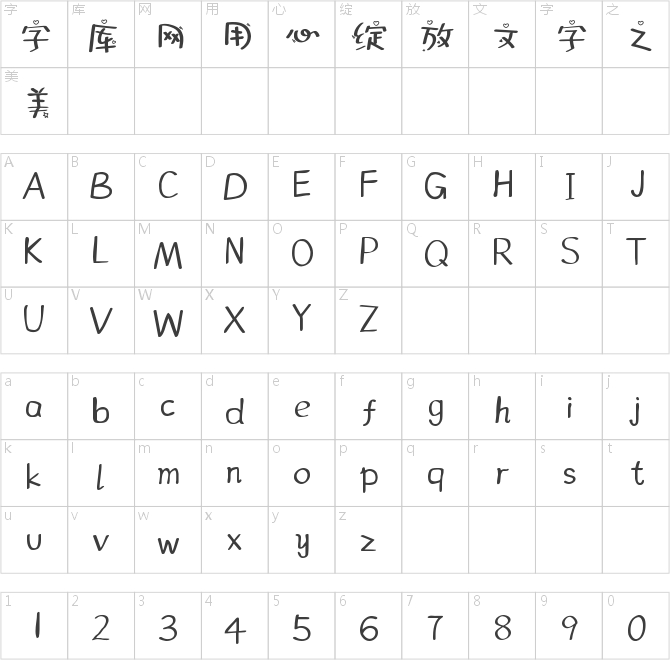
字魂235號(hào)-千紙鶴 詳情頁
字魂235號(hào)-千紙鶴是一款可愛的創(chuàng)意衍生字。字體結(jié)構(gòu)靈活且夸張,不拘一格,筆畫中大量加入了卡通的裝飾,趣味性十足,適用于宣傳設(shè)計(jì)以及商業(yè)類的品牌廣告和產(chǎn)品包裝設(shè)計(jì)。